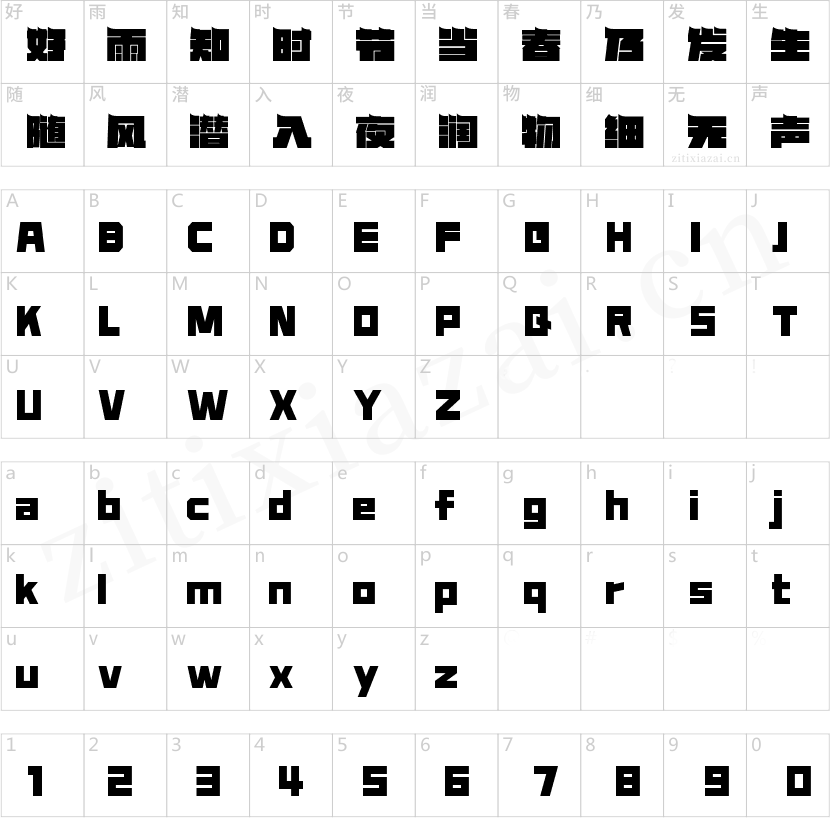
字魂加油体
字魂加油体,这款字体结构工整、笔画清晰,兼顾美观与易读性,适用于标题、正文、海报、包装、LOGO 等多种场景。字形优雅稳定,风格百搭耐看,适配日常排版与创意设计,让文字呈现更舒适、更具质感。字魂加油体一笔一画,皆是细节,以均衡的比例、流畅的线条打造舒适视觉体验,字形端正大气,风格简约现代。无论是商业设计、品牌宣传还是日常排版,都能轻松驾驭,让文字更有格调与力量。字魂加油体字体下载。
字魂字体字魂加油体字体是由字魂创意字库设计并生产的一款可商用的字体,被收录于字魂先锋系列。该字体支持GB-2312标准,包含6942个中文、字母、符号和数字,字体类型偏向黑体,具有时尚的风格,在市面上广泛用于视频综艺、印刷品&包装、活动促销等场景。